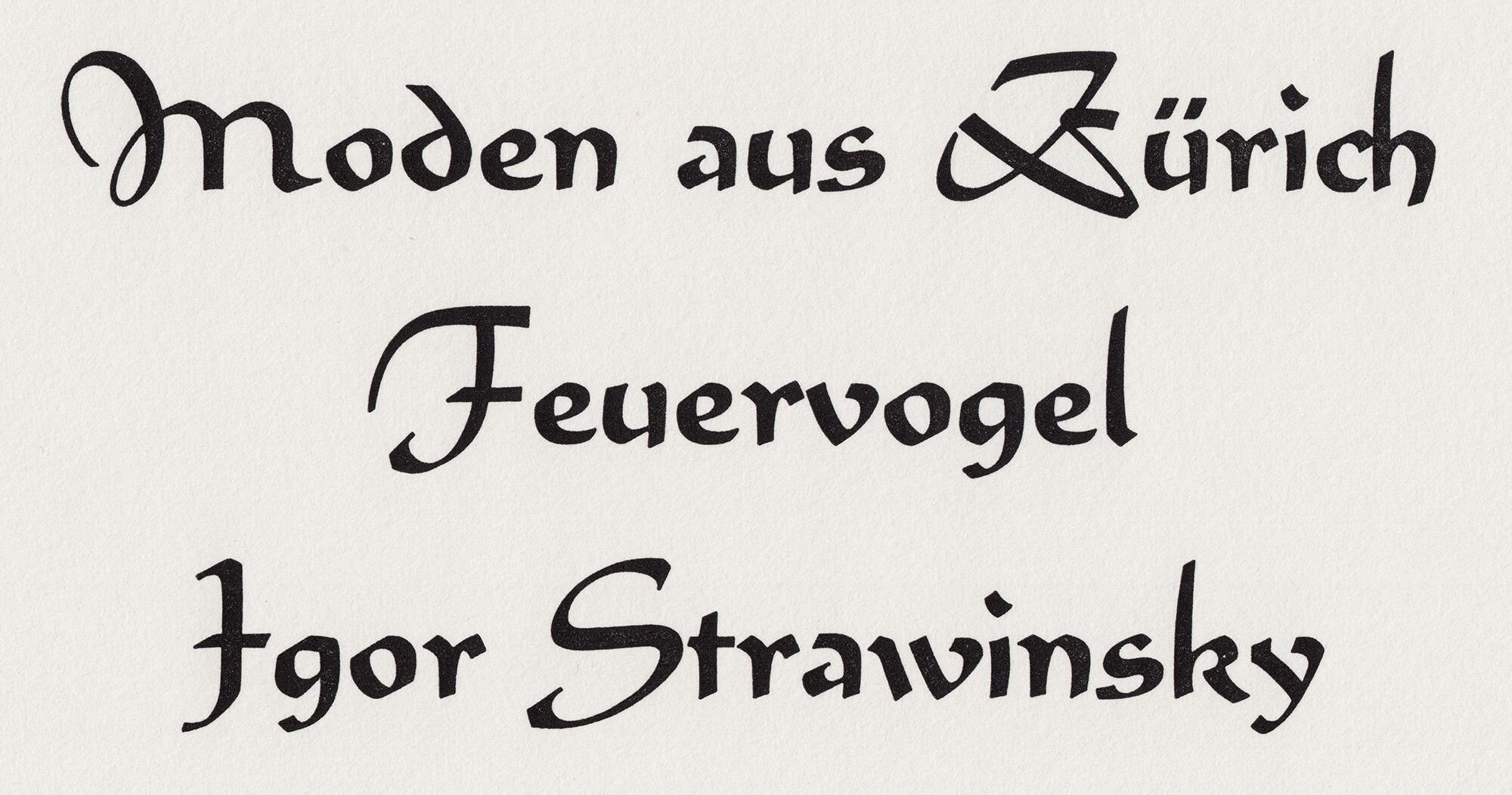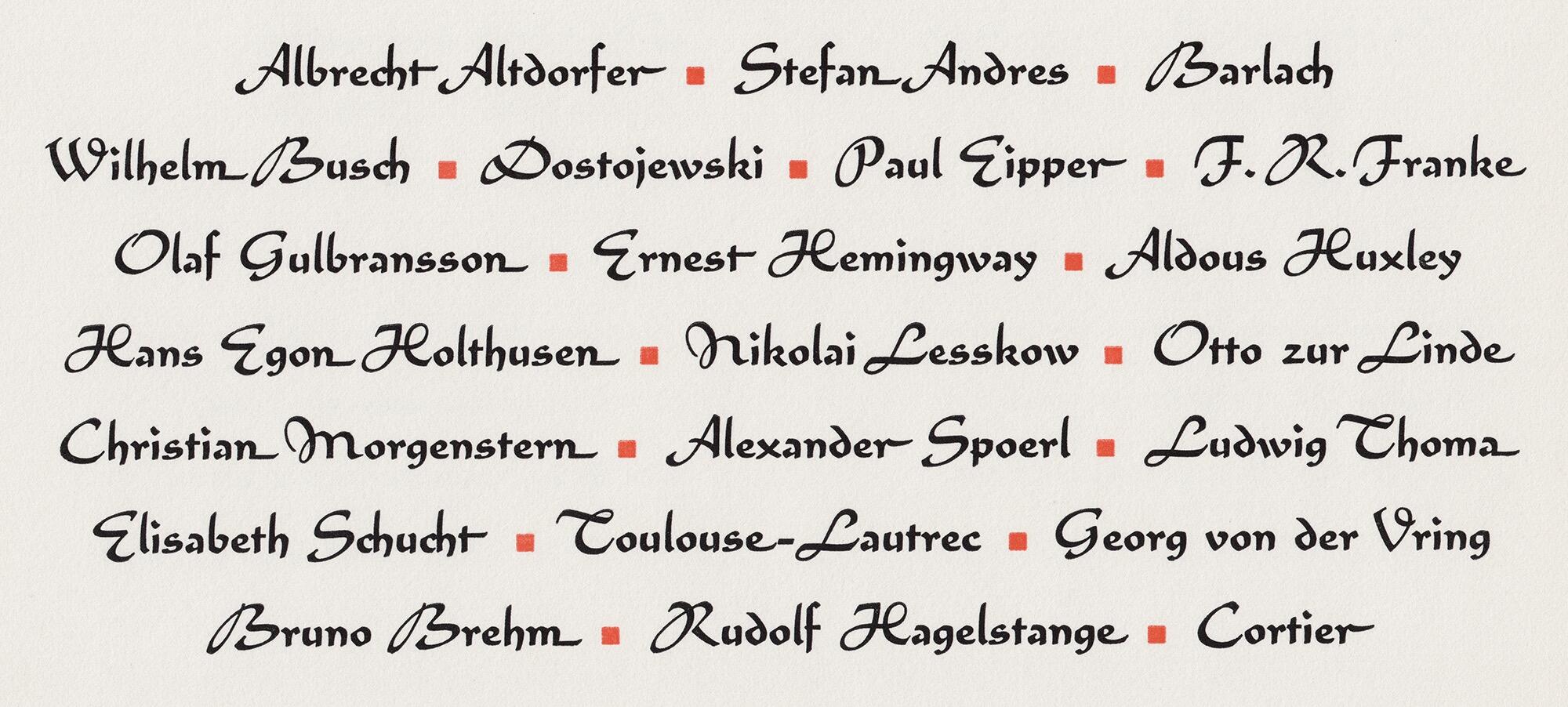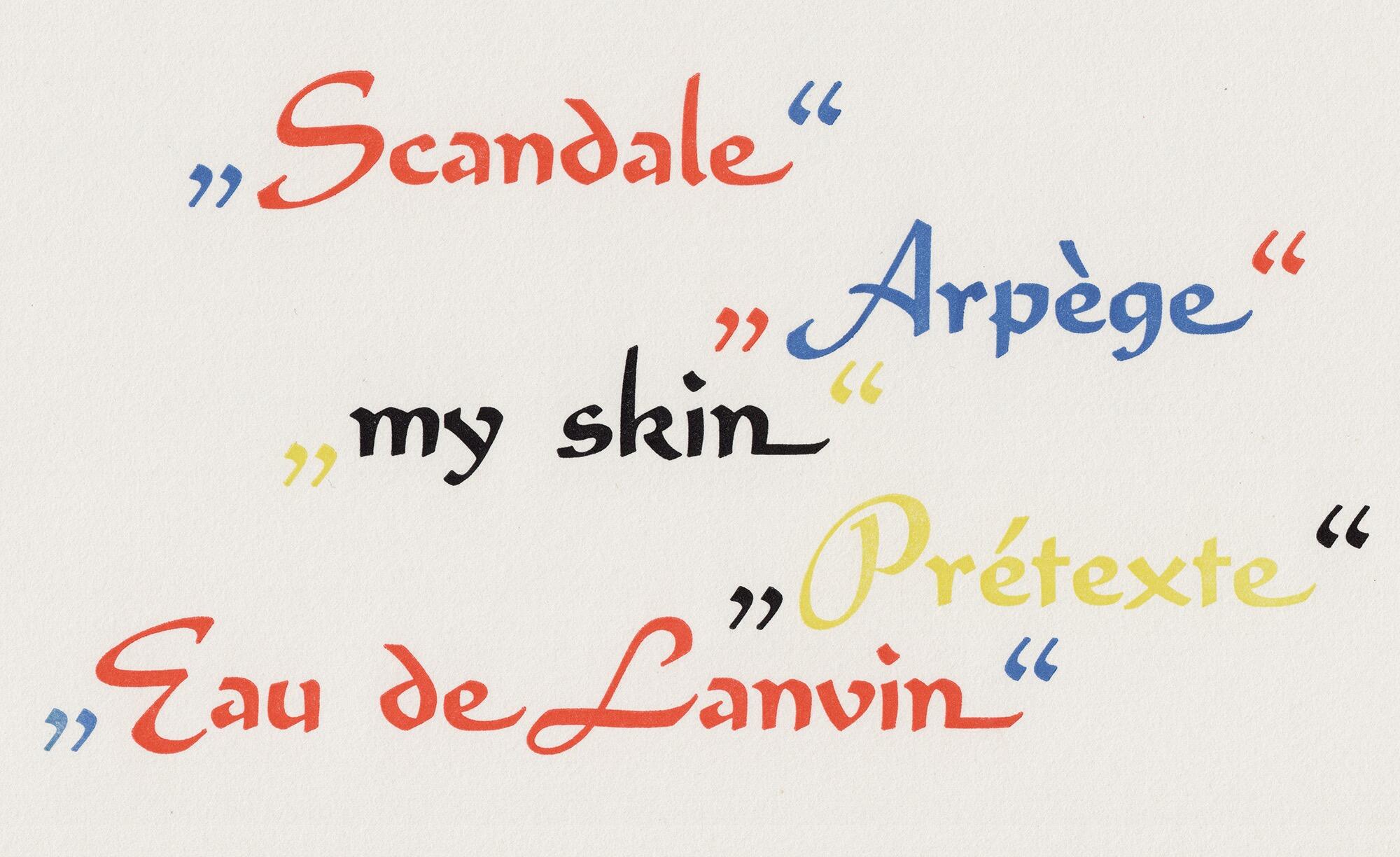
Font-Wiki: Palomba
• 1954
• Antiqua Schreibschrift
Die Palomba ist eine unverbundene, aufrechte Schreibschrift von Georg Trump. Die Schrift erschien in 1954 in einem Schnitt bei C.E. Weber, Stuttgart.
Eine Digitalisierung gibt es als PalombaAR von ARTypes.